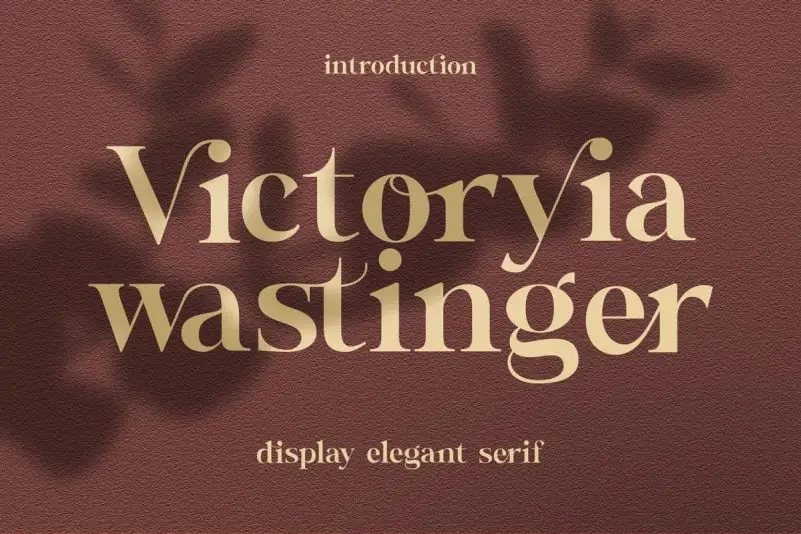
A Wastinger Serif Font é uma elegante tipografia serif que oferece uma experiência única para projetistas digitais apaixonados por detalhes. Criada pela Typetemp Studio, a Wastinger foi desenvolvida com alternativas de tipo e suporte multilíngue, tornando-a ideal para uma variedade de aplicativos gráficos profissionais. Suas linhas perfeitas e sutilezas permitem que designers criem layouts arrojados e sofisticados, atraindo olhares com sua graça natural. Ideal tanto para projetos editoriais quanto para criações de logomarca, etiquetas de roupas ou embalagens de produtos, além de oferecer um background interessante em qualquer imagem de fundo. Com a Wastinger Serif Font, adicione uma pitada de estilo à sua próxima peça visual.